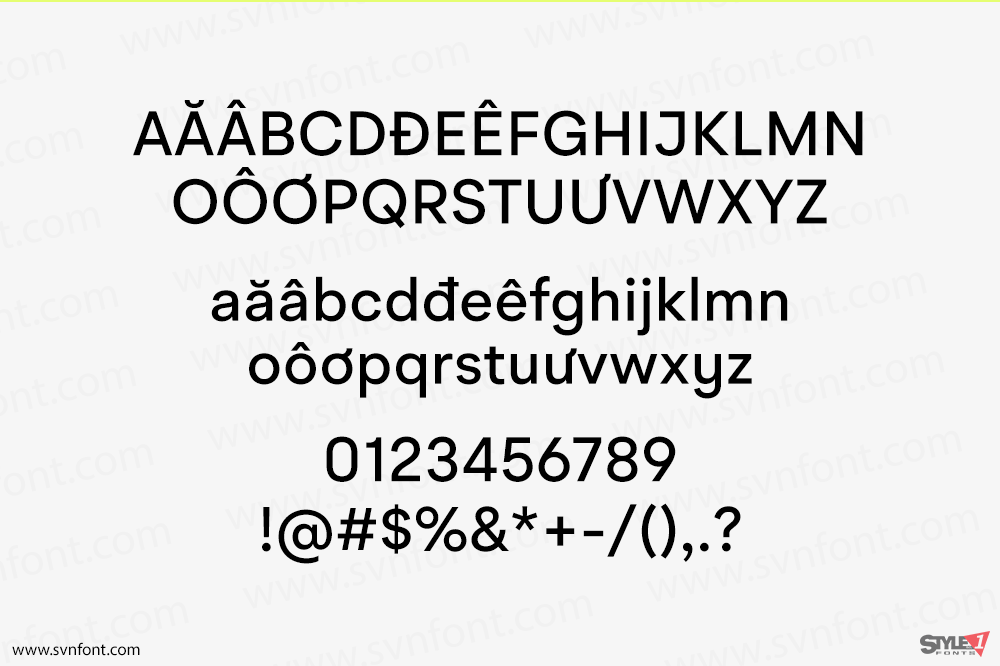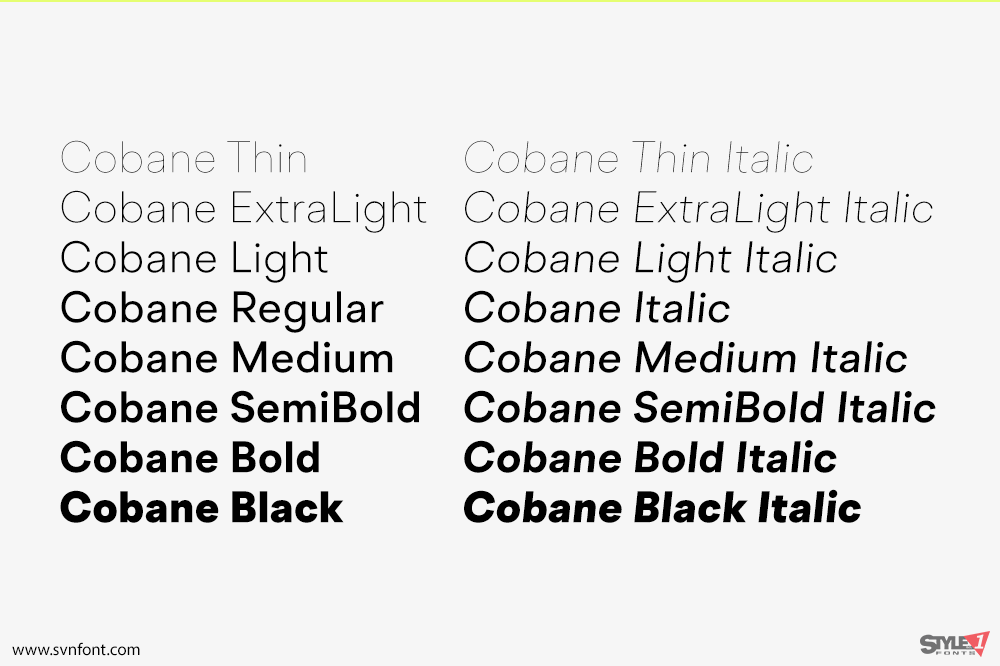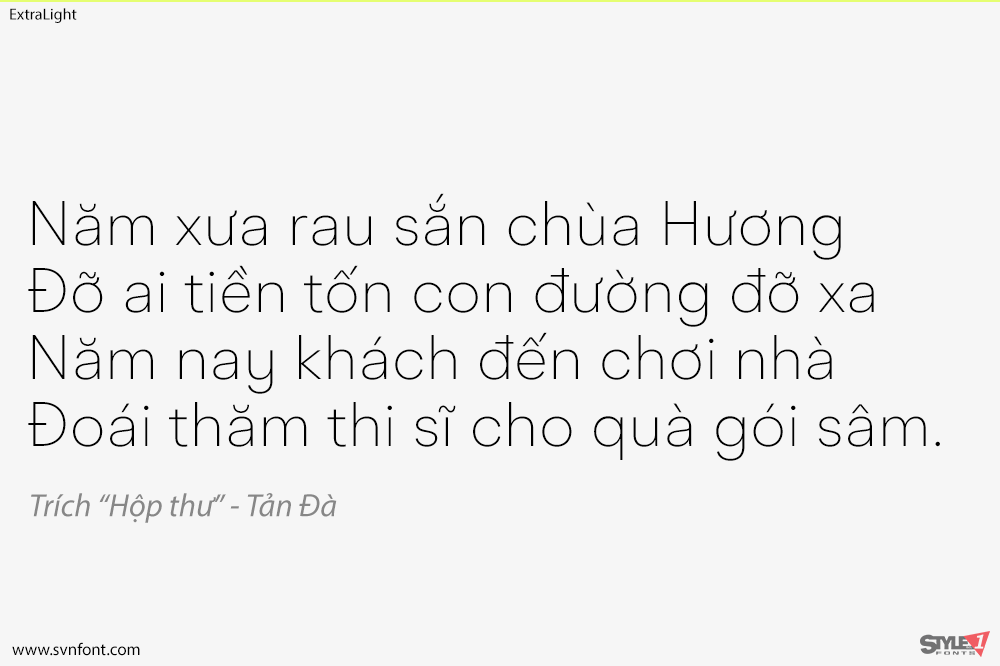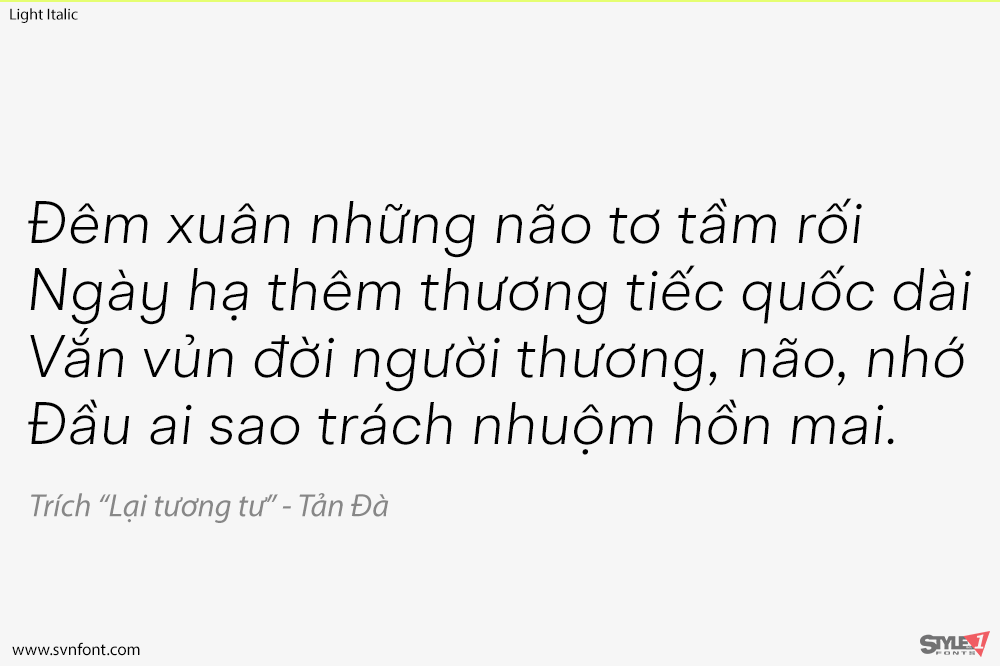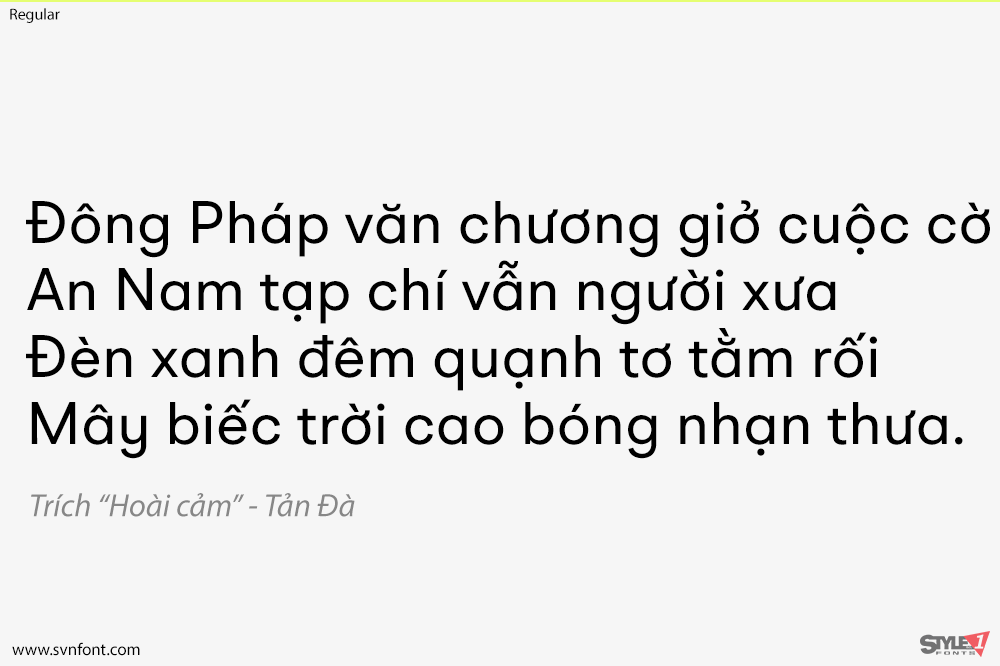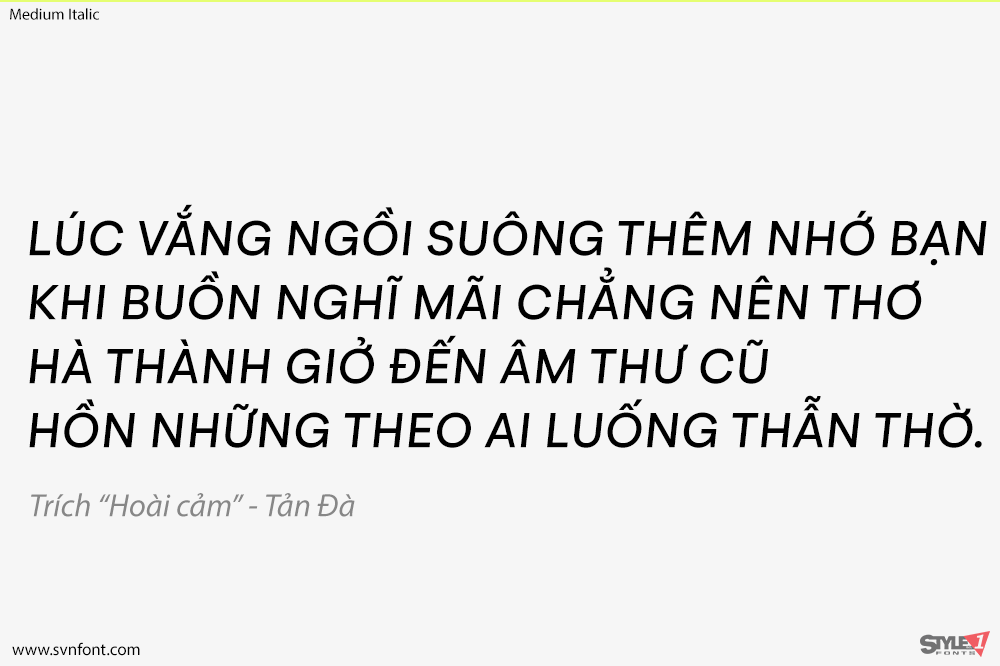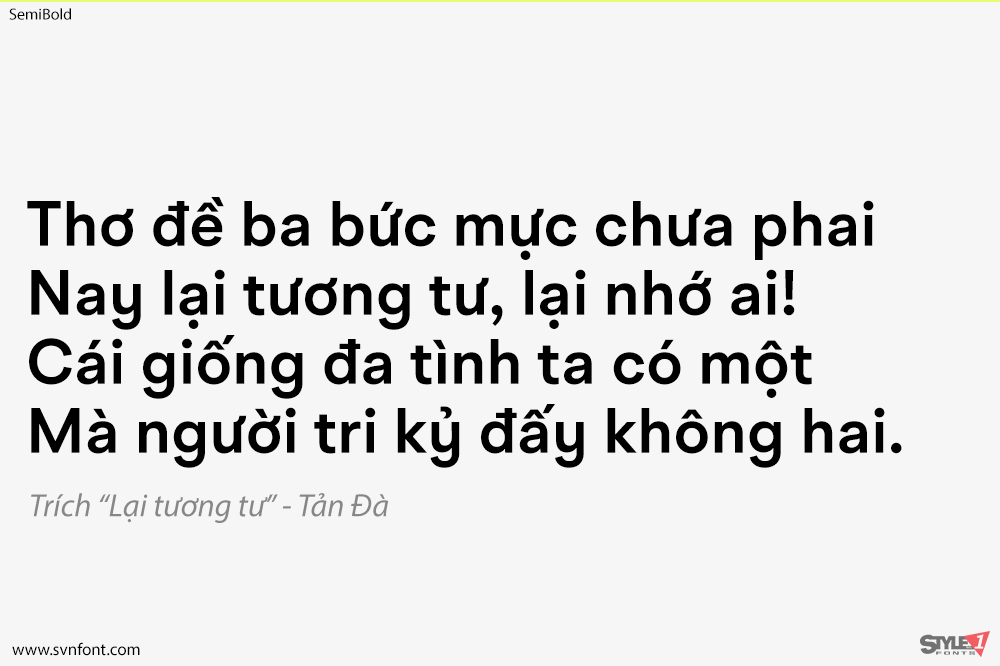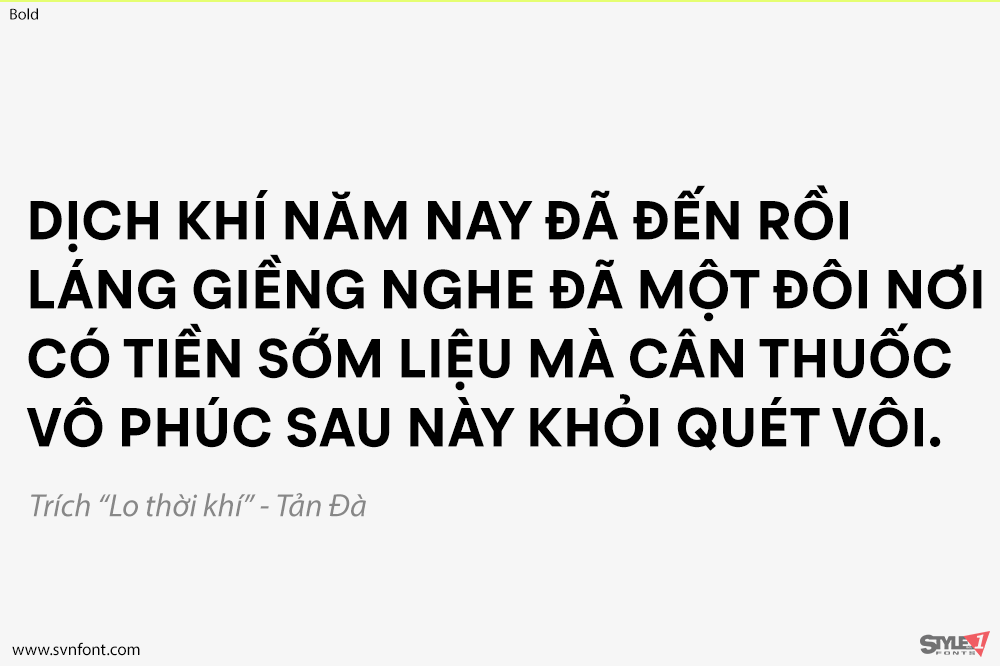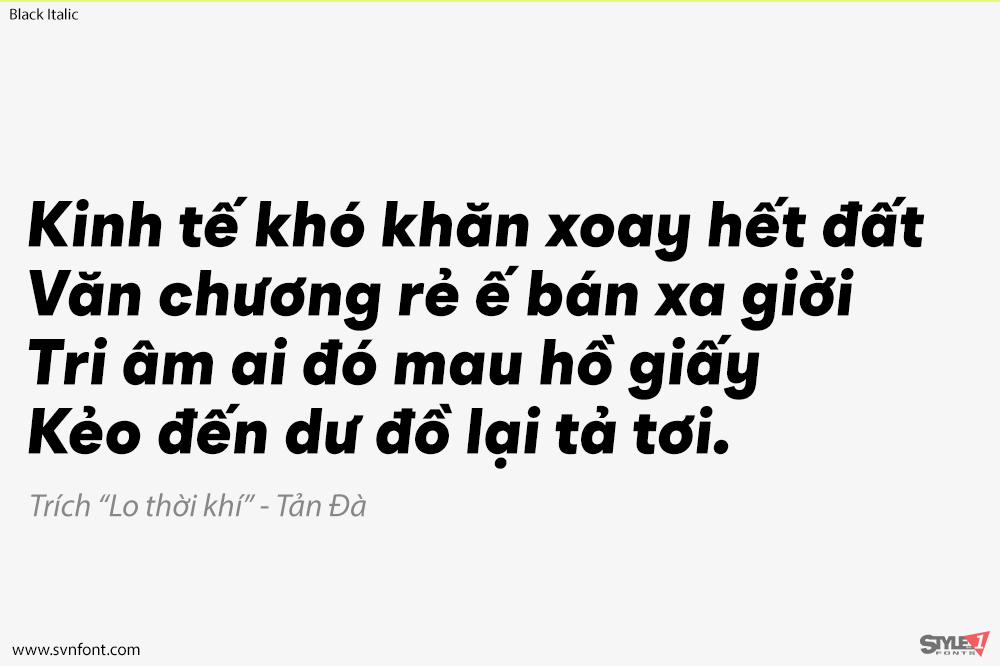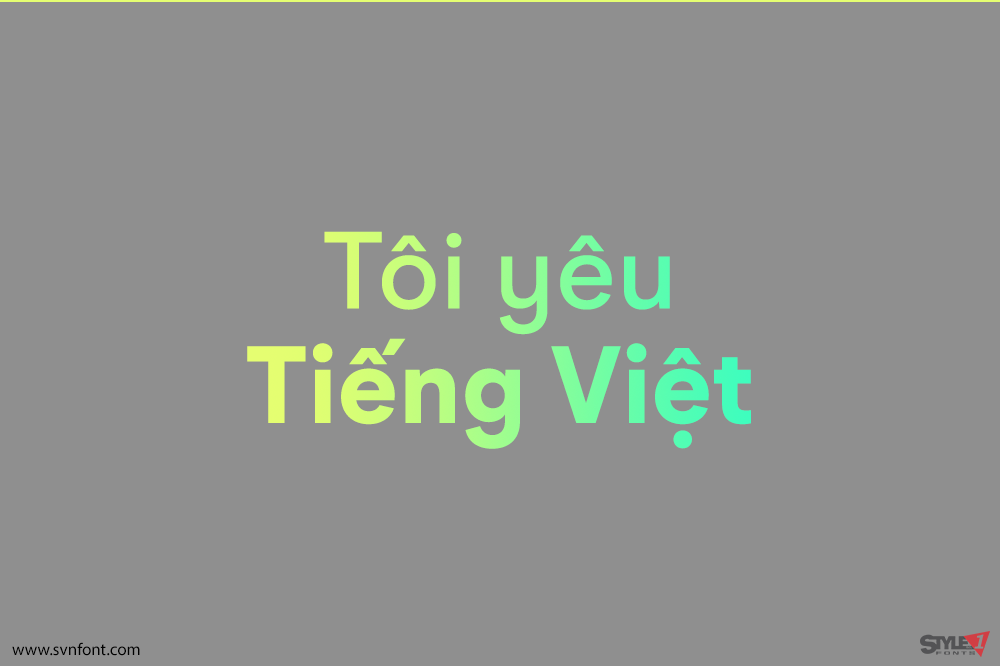
Một họ kiểu chữ neo-grotesque hiện đại gồm 16 kiểu dáng. BR Cobane là sự cân bằng tinh tế giữa chức năng và các đặc điểm đương đại. Được vẽ chính xác với thẩm mỹ hiện đại trong tâm trí, Cobane có những phẩm chất quen thuộc liên quan đến các kiểu chữ grotesques cổ điển, nhưng kết hợp chúng với một hương vị hình học hiện đại mạnh mẽ hơn.
BR Cobane có sẵn trong 16 kiểu dáng được chế tác tinh xảo, với tám độ đậm nhạt từ Thin đến Black. Các font chữ cũng cung cấp hỗ trợ kiểu chữ nâng cao với các tính năng OpenType như các dạng chữ nhạy cảm với chữ hoa/thường (case sensitive forms), biểu tượng (icons), kiểu chữ thay thế (stylistic alternates), số không gạch chéo (slashed zeros) và nhiều bộ chữ số khác nhau (multiple figure sets). Đồng thời cũng chứa hỗ trợ ngôn ngữ nâng cao theo tiêu chuẩn.
Nhà thiết kế: Christoph York
Nhà phát hành: Brink